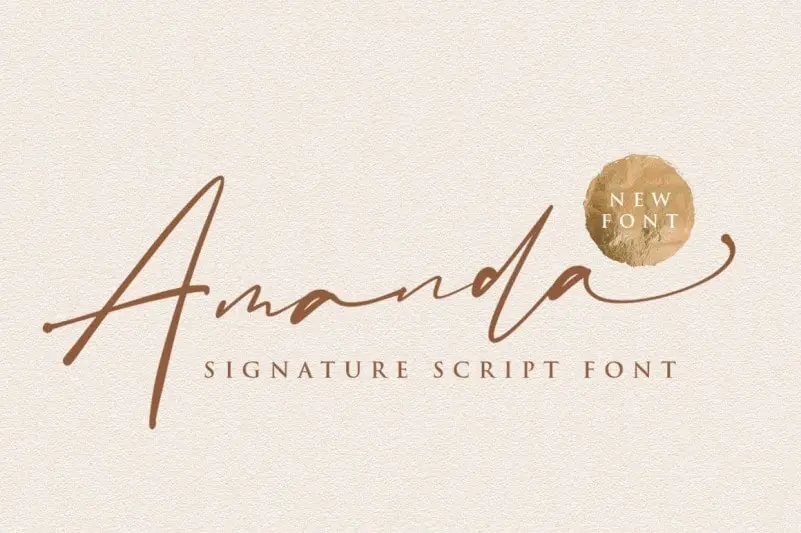
Amanda Handwritten Font – Download Grátis
A Amanda Handwritten Font é uma elegante escolha para aqueles que buscam dar um toque sofisticado a suas criações digitais. Inspirada na escrita cursiva moderna, essa fonte permite que seu texto se torne ainda mais sofisticado e luxuoso, destacando-se em qualquer design. Além disso, ela conta com ligaturas e estilos alternativos para adicionar um toque único ao seu trabalho de forma impactante. Perfectamente adaptada para o formato script, a Amanda Handwritten Font é uma excelente opção para designers buscando dar um novo brilho aos seus projetos, seja em cartazes, banners ou qualquer outro meio digital. Não perca essa oportunidade de adicionar um toque autêntico e moderno ao seu design com apenas um clique.